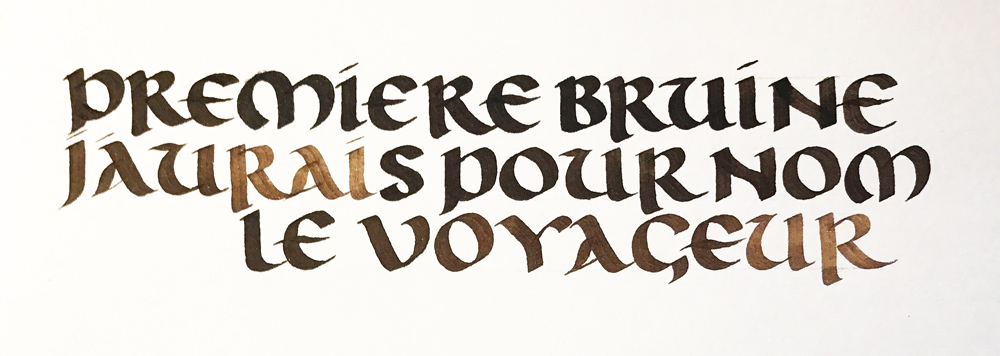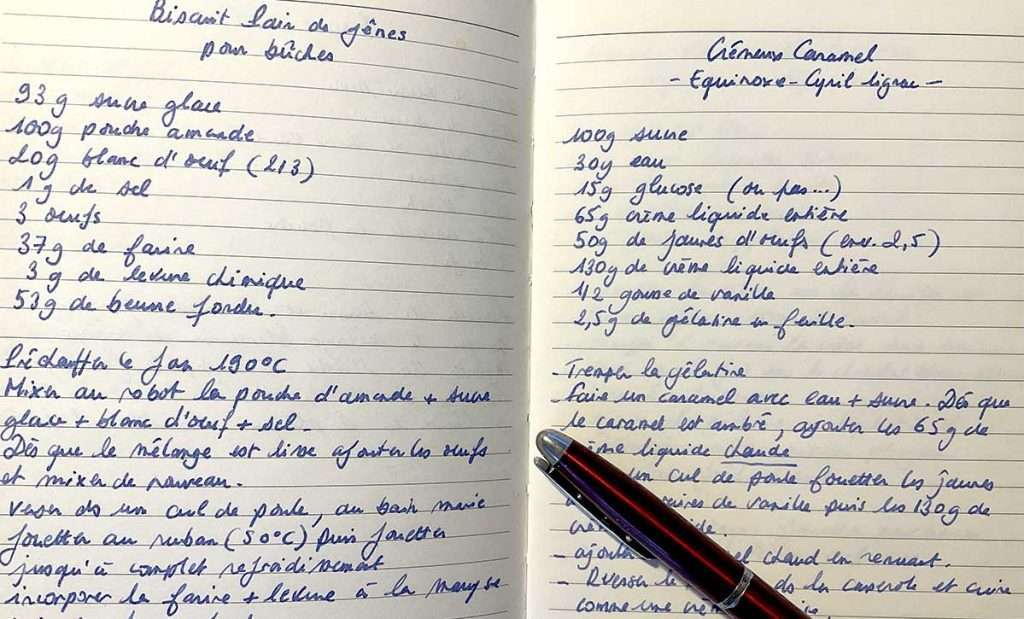
Votre écriture manuscrite n’est pas très soignée, peu lisible ou franchement inesthétique ? Est-ce que l’apprentissage de la calligraphie peut venir à votre rescousse ? Je vous propose quelques réflexions sur le sujet…
L’art de la belle écriture ne nécessite pas… de savoir bien écrire !
Une phrase que l’on entend souvent lorsqu’on pratique la calligraphie est : « Pour arriver à faire ça, il faut déjà avoir une belle écriture au départ ». Evidemment, c’est faux : les calligraphes n’ont pas forcément une écriture manuscrite super belle quand il s’agit de faire leur liste de course ou de prendre des notes à la volée. Cela ne les empêche pas d’avoir une belle main calligraphique, mais cela est le fruit de leur entraînement. De plus, comme nous le verrons plus bas, l’apprentissage de l’écriture et de la calligraphie (au sens artistique du terme), s’abordent de façon différente :
• avec un objectif fonctionnel/utilitaire pour l’écriture manuscrite : savoir prendre des notes, faire une liste, lire un document manuscrit
• avec un objectif esthétique pour la calligraphie
J’y reviendrai plus bas.
Inversement, on m’a une fois demandé : « Est-ce que la pratique de la calligraphie t’a permis d’améliorer ton écriture manuscrite ? ». La réponse est non : mon écriture n’a pas évolué depuis mes années lycées. Malgré des années de pratique de la calligraphie, rien n’a changé dans mon écriture de tous les jours. Cependant, j’avais toujours été attentive à mon écriture que j’avais pas mal peaufiné et surtout j’ai toujours adoré écrire à la main.
Sans phare, mon écriture de tous les jours qui est loin loin d’être « calligraphique » !
La pratique de la calligraphie : une façon de surmonter le vécu scolaire
Maîtriser l’écriture cursive est un apprentissage complexe
Beaucoup de personnes ont un vécu un peu douloureux ou stressant avec l’écriture cursive : l’apprentissage de l’écriture est une des activités motrices les plus complexes à intégrer pour un enfant. Cela mobilise en effet des capacités psychomotrices qui ne sont pas du tout innées, et qu’il faut beaucoup entraîner. Il n’est pas incongru de penser que pour certains, cet apprentissage est même douloureux physiquement et psychologiquement, d’autant plus s’il n’est pas bien guidé. L’acquisition du geste, pour reproduire la forme de la lettre, peut être très contraignant, fatiguant et crispant.
Au-delà de la difficulté à maîtriser le geste, produire un résultat inesthétique et/ou illisible met un sacré coup de canif dans l’égo du petit enfant qui a fait tant d’effort. Au fil des années, une écriture « pas jolie » finit par vous coller aux semelles comme un vieux chewing-gum :
• D’abord les profs grimacent à chaque fois que vous leur tendez une copie (alors que vous êtes déjà mortifié(e) de rendre un écrit aussi moche)
• Les copains/copines se moquent de vous
• Vos parents se désespèrent devant vos cahiers
• Vous avez du mal à relire vos notes parce que vous avez galéré puissance 10 pour les prendre tout en écoutant le cours;
• Une fois adulte, vous écrivez des lettres de motivations qui seront dézinguées par des graphologues vicieux (ceux qui demandent encore des lettres manuscrites) et vous feront louper le job de vos rêves;
Autant de situations finalement dans lesquelles l’écriture est synonyme d’humiliation, d’échec et de pénibilité. Le passage au clavier, à cet égard, est un don des dieux, un instrument d’égalité, aussi.
Quand le désir d’écrire s’invite à nouveau
Pour autant, le désir d’écrire, pour soi, peut ressurgir à tout moment. Ce peut-être dans le cadre d’une démarche de développement personnel (écriture d’un journal), pour écrire à quelqu’un à qui on tient (ou à un graphologue vicieux), pour consigner ses pensées, ses idées… Eventuellement cela peut servir le jour où vos tablettes, téléphones et autres outils numériques n’ont plus de batterie. Mais attention, la bête noire refait surface : cette écriture qui vous a fait honte toute votre  vie, ou cette difficulté à tenir un stylo plus de 10 minutes sans avoir une crampe.
C’est à ce moment que la calligraphie peut aider à surmonter les difficultés que l’on a pu rencontrer avec l’écriture manuscrite apprise à l’école.
Calligraphier, c’est vivre l’écriture autrement
Tout d’abord, l’apprentissage de la calligraphie latine ouvre une toute nouvelle perception de ce qu’est une simple lettre. En commençant par le début, avec par exemple une onciale tracée avec un outil assez large comme un calame, on expérimente quelque chose de totalement nouveau :
• prise de conscience des formes, des espaces blancs;
• prise en main d’un outil spécifique et original : plume, calame
• fluidité de l’encre, le bruit de l’outil sur le papier;
• révélation de la forme tracée, etc.
On est loin du combo bic bleu/cahier Seyès (d’ailleurs, si vous souhaitez améliorer votre écriture, commencez par fuir le stylo bille !).
Quelque part, le geste d’écriture est plus ludique et le rendu totalement esthétique et artistique. Et ça, avouons-le, on l’a rarement vécu en classe !
Pratiquer la calligraphie permet d’aborder l’écriture avec un œil nouveau. On peut apprendre à aimer les lettres. On peut découvrir le plaisir de se concentrer sur un tracé et de le réussir. On peut constater les progrès après avoir fourni les efforts nécessaires pour s’améliorer. On peut réapprendre les gestes. On peut (re)découvrir le plaisir d’écrire, de poser des mots sur le papier, de les transmettre à quelqu’un, tout simplement.